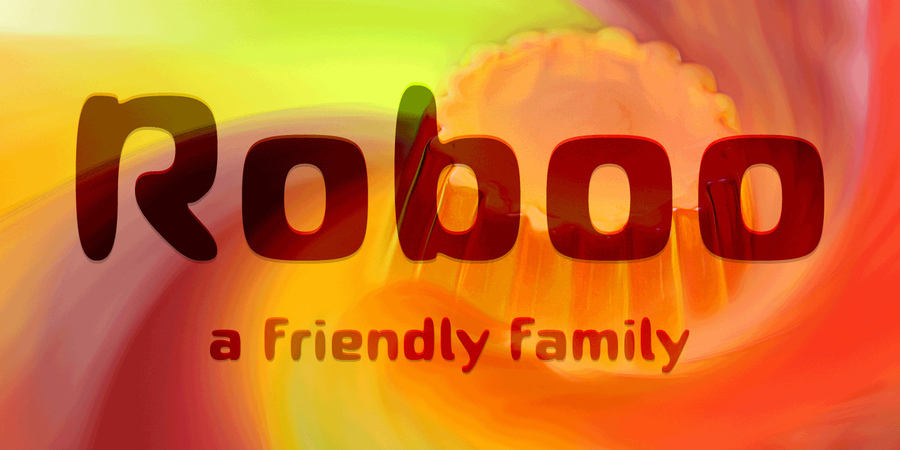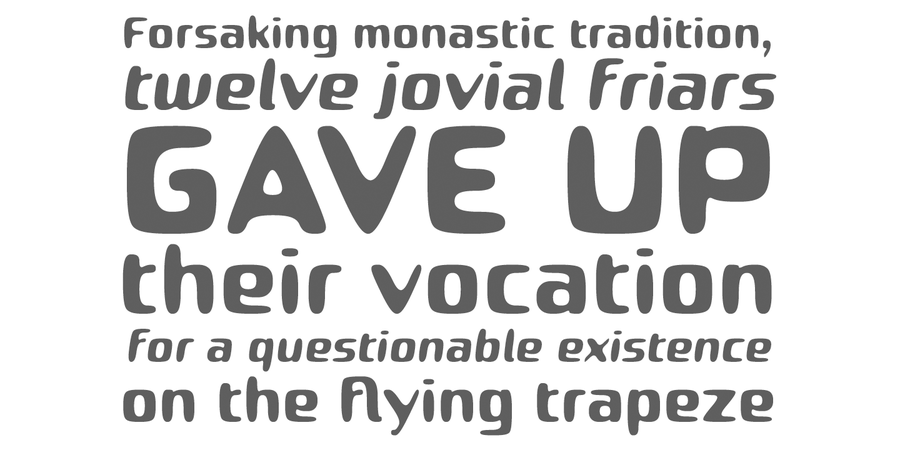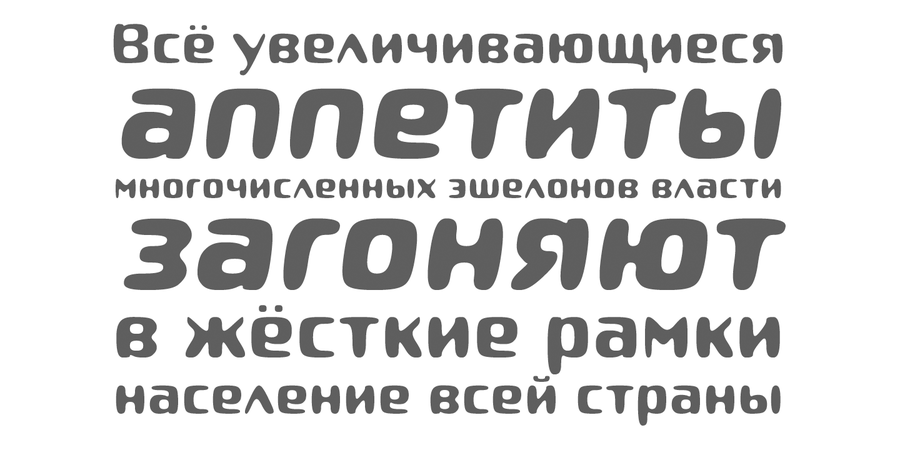
Опис гарнітури Roboo 4FШрифт Робу дружелюбен и обаятелен и обладает хорошей разборчивостью. Шрифт включает четыре начертаня с многоязычным комплектом символов. Робу отлично подходит для рекламы, упаковки подуктов питания и различных товаров для детей. Разработан Сергеем Ткаченко в 2014 году.
Асоціації з сімейством шрифтів Roboo 4FОсобистість і характер гарнітури:
добродушний, доброзичливий, М'який, привітний, довірчий, добрий, позитивний, милий, молодіжний, оригінальний, плавлений, гладенький, статичний, веселий, смішний, пустотливий, свіжий, стиглий, смачний, простодушний, дитячий, мультяшний, святковий, надувний, соковитий, грайливий, симпатичний, хлоп'ячий, спекотний, сильний, мотивуючий, домашній, гумовий